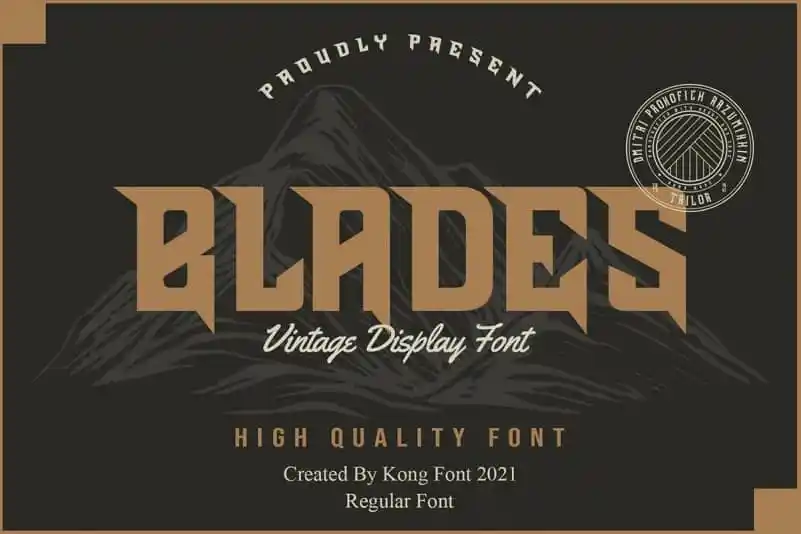
Blades Display Font – Fonte Grátis
Blades Display Font
A Blades Display Font é uma elegante escolha para quem busca um estilo que reflete a modernidade e sofisticação. Inspirada no design atualmente popular, ela surge como a perfeita resposta para todos os conceitos e ideias lançados nesta era moderna. Com seu peso reduzido, esta fonte exibe linhas afiadas e traços finos, proporcionando um visual atento e assertivo que se adequa perfeitamente tanto em headlines quanto em subtítulos de design gráfico ou branding. Ideal para quem busca uma fonte com personalidade forte e versátil, Blades Display captura a essência da atualidade, mantendo-se ao mesmo tempo elegante e reconhecível. Suas linhas incisivas remetem à ideia de força, destreza e determinação que permeiam nosso mundo tecnológico e rápido. Perfecta para usar em materiais gráficos digitais ou presenciais, a Blades Display Font é uma escolha inteligente para aqueles buscando um design moderno e atento no seu próximo projeto visual.